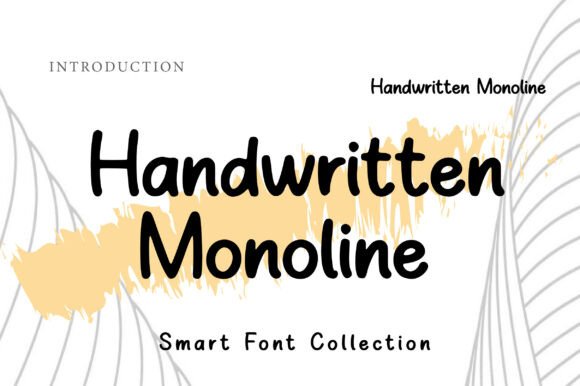
Handwritten Monoline
Handwritten Monolineのような高品質の素材をお探しの場合、このプレミアムパッケージはクリエイティブなプロジェクトに素晴らしい選択です。
POD(オンデマンド印刷)製品、結婚式の招待状、またはソーシャルメディアのグラフィックを作成している場合でも、Handwritten Monolineは理想的です。